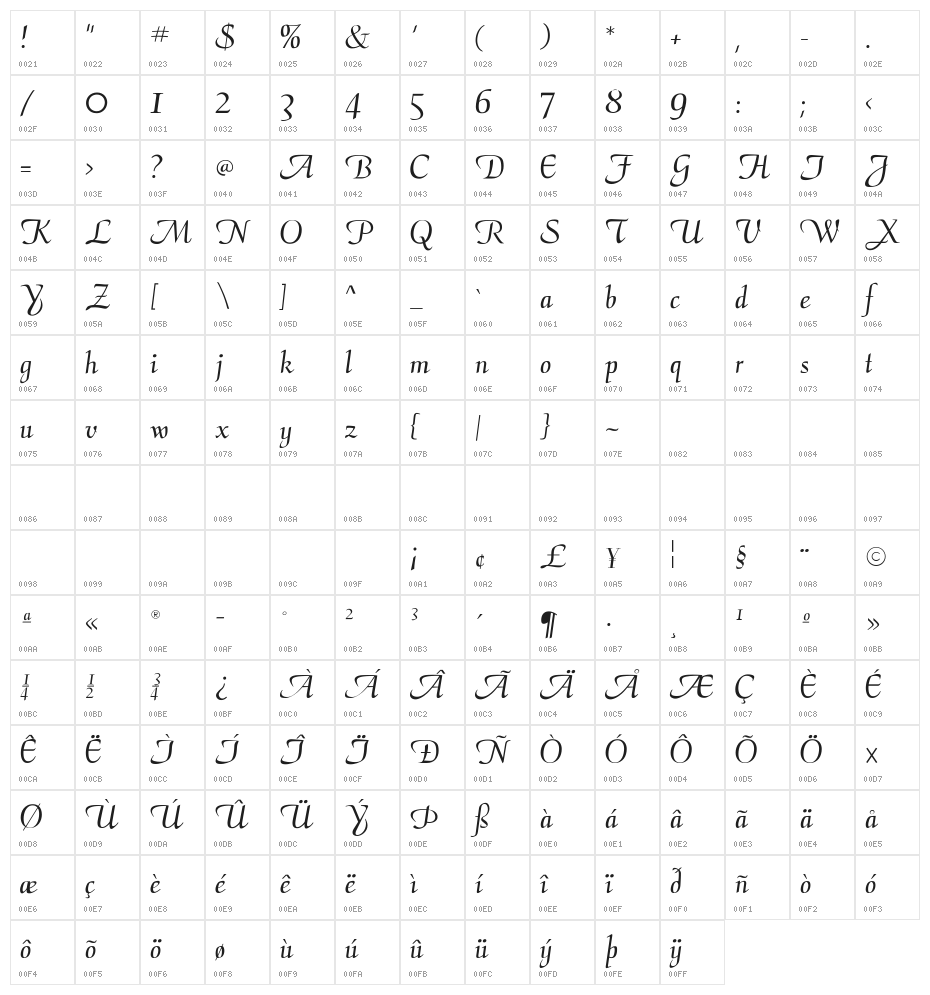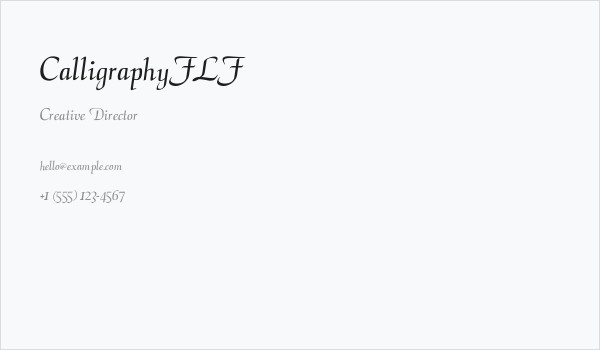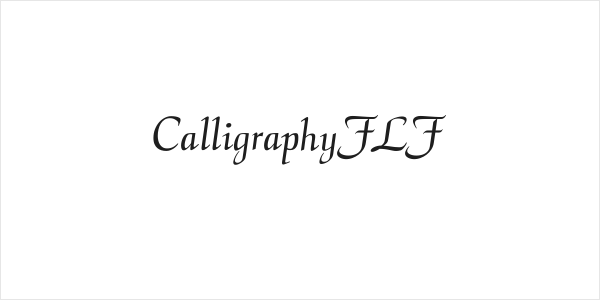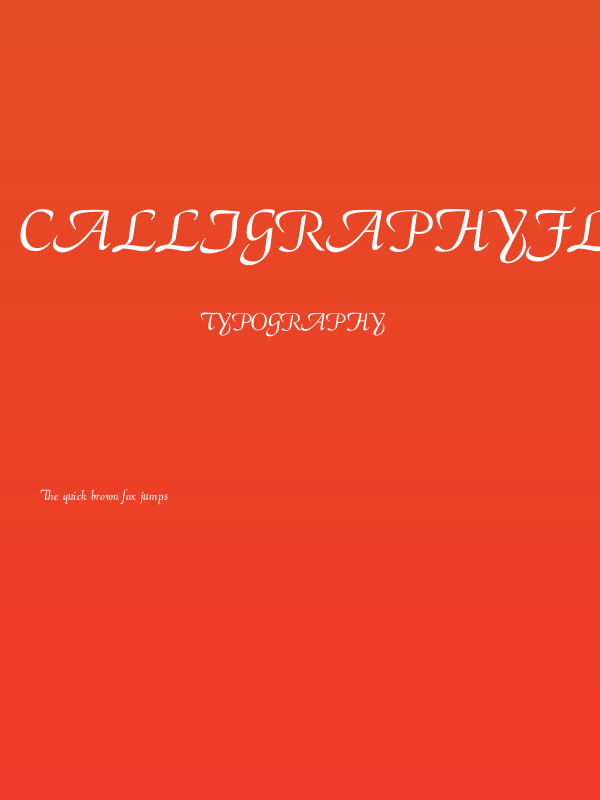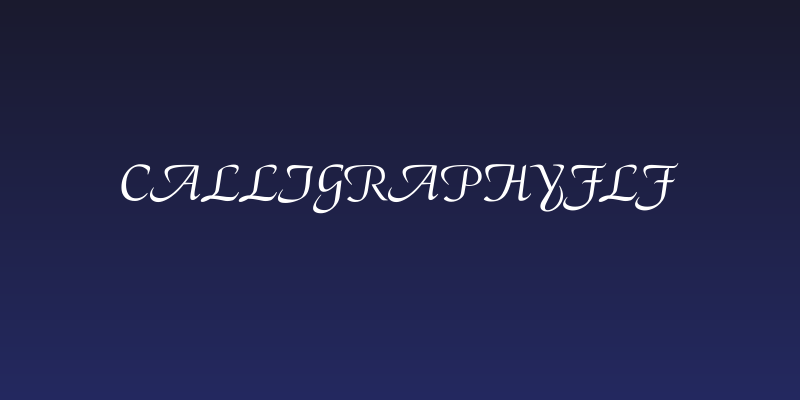
CalligraphyFLF Font
✎ Calligraphic
| Kategorien | Calligraphic |
| Gesamtstil | Classic |
| Anwendungsfall | Headlines, Invitations, Artistic projects |
| Vorgeschlagene Projekte | Ideal for wedding invitations, elegant branding, artistic projects, and formal stationery. |